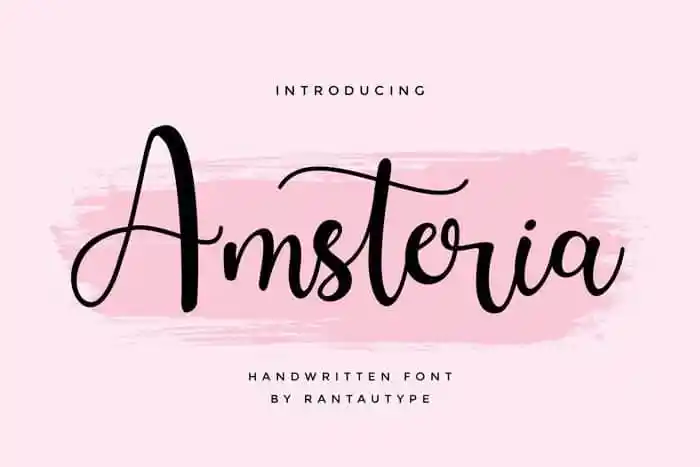
Amsteria Calligraphy Font – Download Grátis
A Amsteria Calligraphy Font é uma fonte script que traz atraente e natural expressão do desenho à mão. Ideal para criar textos elegantes e agradáveis ao olhar, cada caractere foi cuidadosamente trabalhado pelo designer Rantautype. Esta fonte é perfeitamente adaptada para uso em cartas de convite, marca e design de publicidade, bem como para folhetos e outras aplicações visuais. Com seu formato PUA (Unicode Private Use Area) codificado, todos os caracteres da Amsteria Calligraphy Font podem ser acessados através do Character Map, do próprio programa de fontes ou qualquer outro gerenciador de fonts que você prefira. A Amsteria Calligraphy é uma fonte versátil e profissional para quem deseja incorporar um toque artístico à sua designação visual.